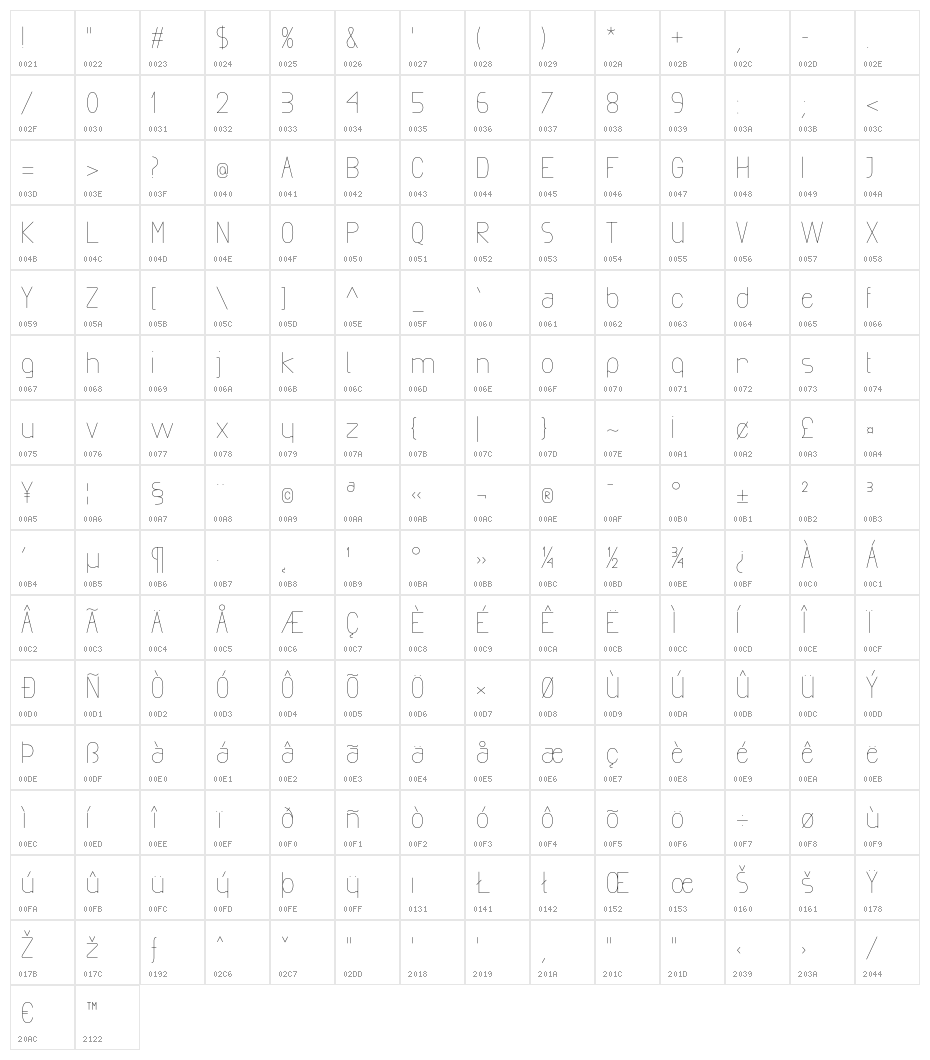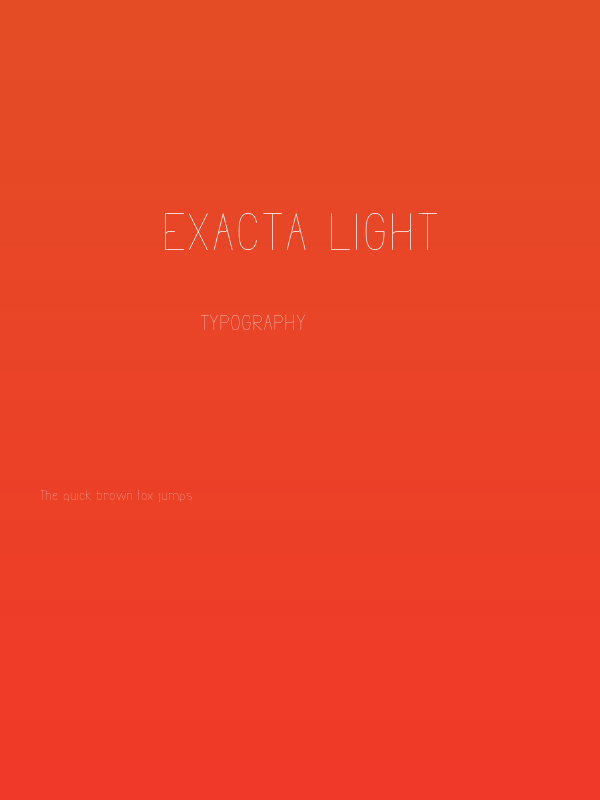
Exacta Light Font
✎ Modern
| Progetti proposti | Ideal for modern branding, minimalist design projects, tech-related content, and clean editorial layouts. |